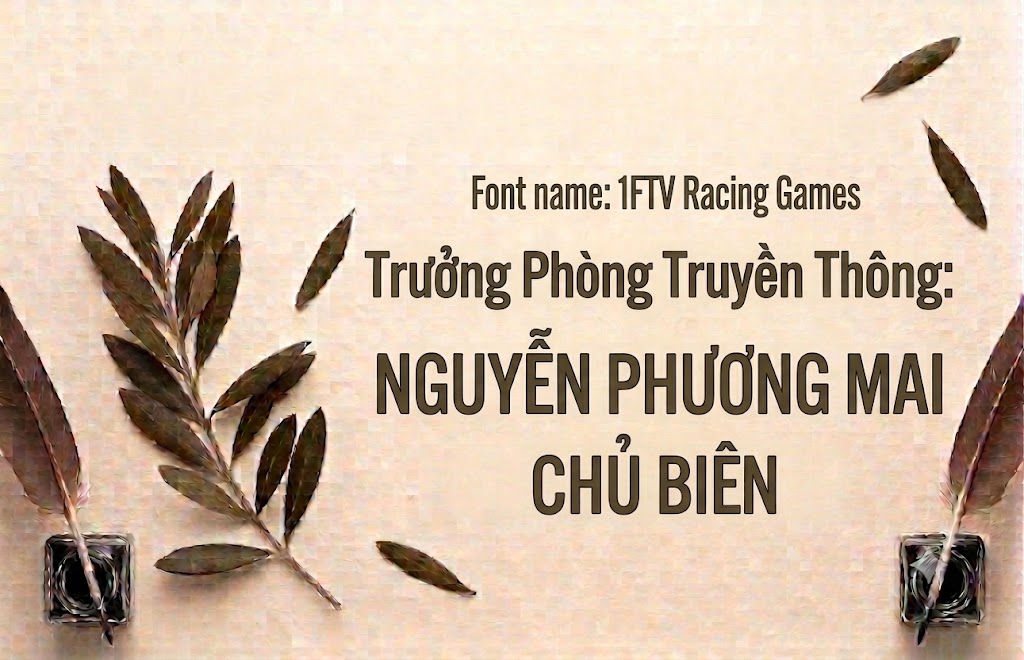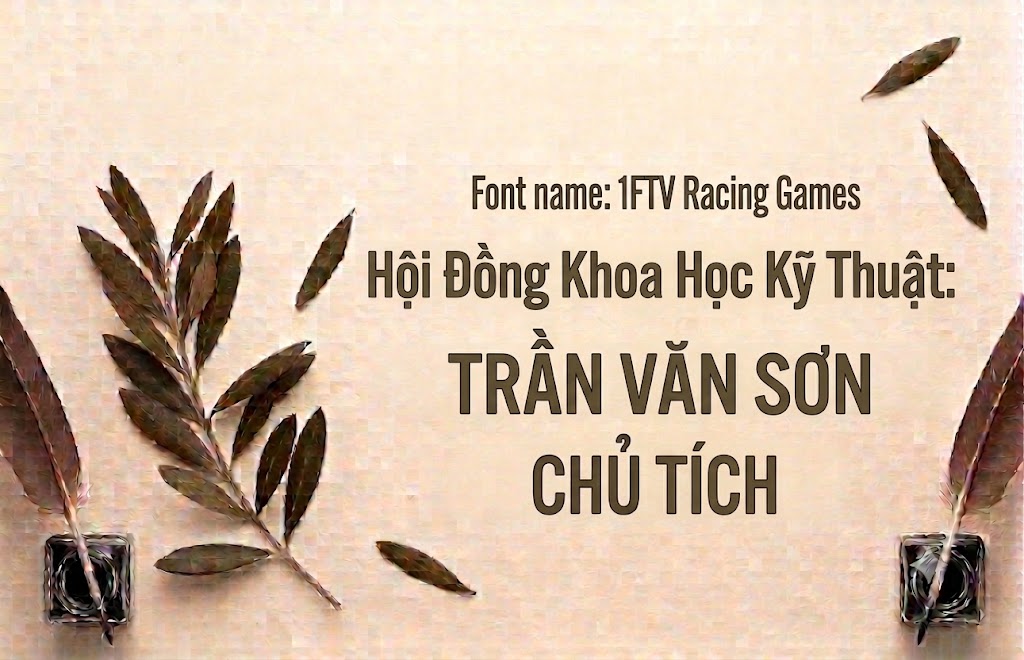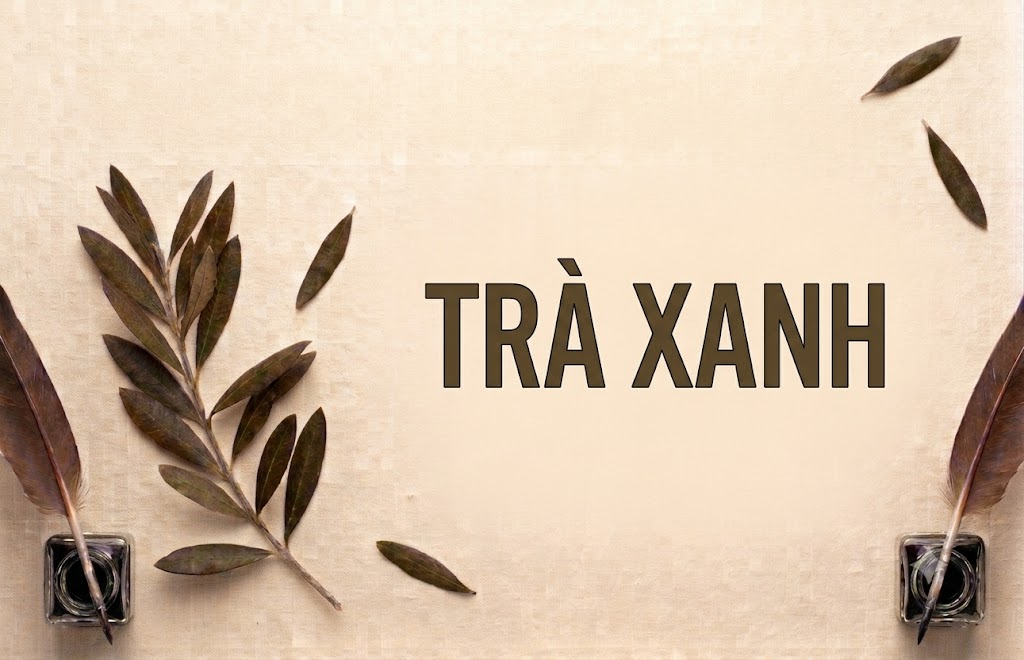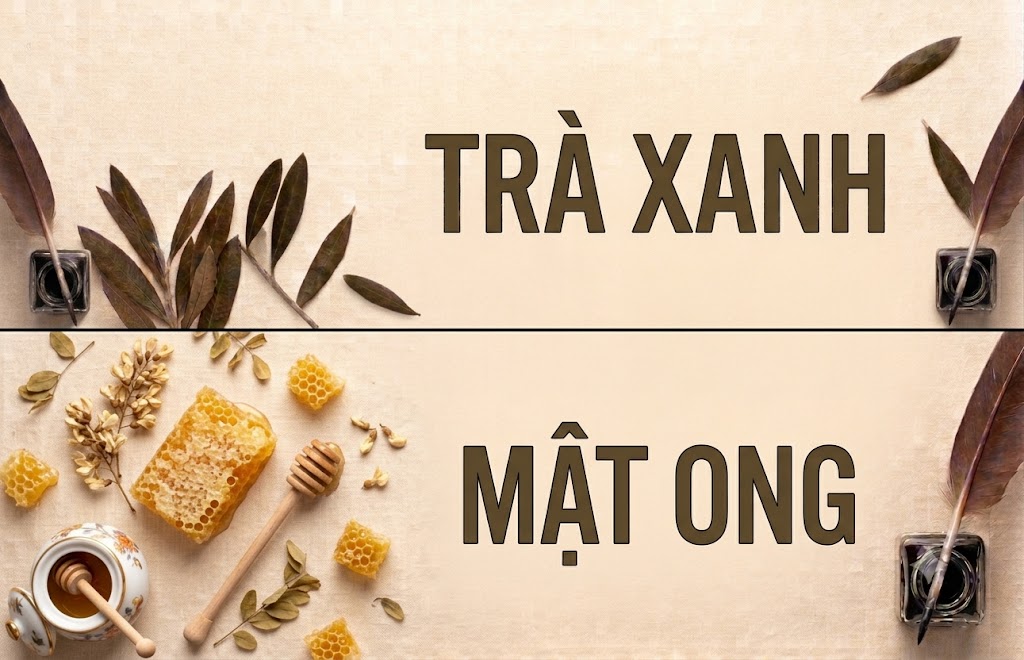
1FTV Racing Games
Trong các dự án thiết kế liên quan đến ngành game hay các bộ môn thể thao tốc độ, việc lựa chọn một phông chữ thể hiện được sự mạnh mẽ và tinh thần bứt phá là vô cùng quan trọng.
Một kiểu chữ quá mềm mại hoặc thô cứng thông thường sẽ khó lòng truyền tải được cảm giác chuyển động nhanh và năng lượng dồi dào của thương hiệu.
Nếu bạn đang tìm kiếm một giải pháp chữ khối nghiêng độc đáo để làm nổi bật các dự án của mình, thì font 1FTV Racing Games chính là câu trả lời hoàn hảo.
Giới thiệu về font 1FTV Racing Games
Font 1FTV Racing Games là một phông chữ hiển thị không chân mang phong cách thể thao, hiện đại và tràn đầy động lực chuyển động.
Nhờ các thông số kĩ thuật tối ưu này, phông chữ có khả năng hiển thị vô cùng sắc nét, giúp bạn tự tin ứng dụng trên mọi phần mềm đồ họa hiện đại mà không sợ lỗi vỡ hình.
Đặc điểm nổi bật của phong cách thiết kế Racing Games
Sức hút lớn nhất của font 1FTV Racing Games đến từ cấu trúc chữ góc cạnh mạnh mẽ kết hợp cùng độ nghiêng đầy năng lượng và tốc độ.
Điểm cộng rất lớn của bộ font này là việc hỗ trợ trọn vẹn cả hệ thống chữ thưCác chữ cái được tạo hình với những đường vát nhọn táo bạo ở các góc, mô phỏng phong cách của các trò chơi điện tử đua xe hoặc các biểu tượng giải đấu thể thao lớn.ờng bên cạnh bộ chữ viết hoa cơ bản, mang lại sự linh hoạt tối đa khi sắp xếp bố cục văn bản.
Độ dày nét chữ thuộc nhóm bold đậm nét, kết hợp với phom dáng khí động học giúp dòng tiêu đề của bạn luôn nổi bật và thu hút thị giác cực mạnh.
Để phông chữ vận hành mượt mà trên mọi hệ thống máy tính, phiên bản font 1FTV Racing Games đã trải qua quy trình xử lý thông số kĩ thuật kỹ lưỡng.
Hệ thống khoảng cách chữ và độ giãn dòng đã được căn chỉnh chuẩn xác, giúp các từ khi đứng cạnh nhau luôn giữ được sự liền mạch và thẩm mỹ tốt nhất.
Bên cạnh hệ thống chữ cái hoa và thường đồng bộ, phông chữ còn tích hợp đầy đủ dãy số từ 0-9 cùng hệ thống các ký tự đặc biệt, dấu câu thông dụng (1234567890.:,;'"(!?)+-*/=).
Bản Việt hóa này giúp bạn hoàn toàn yên tâm sáng tạo các nội dung tiếng Việt cho video ngắn hay banner quảng cáo mà không lo gặp phải tình trạng lỗi hiển thị.
Hình ảnh demo thực tế của font 1FTV Racing Games
Để giúp bạn dễ dàng hình dung khả năng co giãn và hiển thị linh hoạt của phông chữ này trên các kích thước khác nhau, hãy cùng xem qua bảng mô phỏng thực tế:
Kích thước nhỏ (12pt – 24pt): Các nét chữ đậm và góc nghiêng thể thao vẫn hiển thị rất rõ ràng, ngay ngắn, dễ đọc trên màn hình điện thoại di động.
Kích thước lớn (36pt – 72pt): Đây là không gian lý tưởng để font chữ phô diễn toàn bộ sự mạnh mẽ, tạo hiệu ứng thị giác bứt phá cực mạnh cho các tiêu đề chính.
Ứng dụng của font Racing Games trong thiết kế đồ họa và làm video
Sở hữu nét cá tính bứt phá và cấu trúc hoa – thường linh hoạt, font 1FTV Racing Games mở ra không gian ứng dụng rộng lớn cho các dự án truyền thông:
Thiết kế thumbnail Youtube và ảnh thu nhỏ mạng xã hội: Đây là vũ khí hạng nặng để tăng tỷ lệ nhấp chuột cho các chủ đề về esports, game đua xe, công nghệ hoặc các nội dung hành động mạnh mẽ.
Làm tiêu đề video ngắn (Tiktok, Shorts, Reels): Cấu trúc chữ nghiêng góc cạnh giúp các câu từ khóa chính hay tiêu đề mở đầu video trở nên vô cùng bắt mắt và giữ chân người xem lướt chậm lại.
Banner và poster quảng cáo giải đấu: Hoàn hảo cho các poster giải đấu thể thao, banner câu lạc bộ gym, fitness, xe độ hoặc các sự kiện quảng bá sản phẩm có tính năng động, bứt phá.
Nhận diện thương hiệu phong cách năng động: Phù hợp làm logo dạng chữ khối, artwork in ấn cho các thương hiệu thời trang streetwear hoặc nhãn hàng đồ nam cá tính.